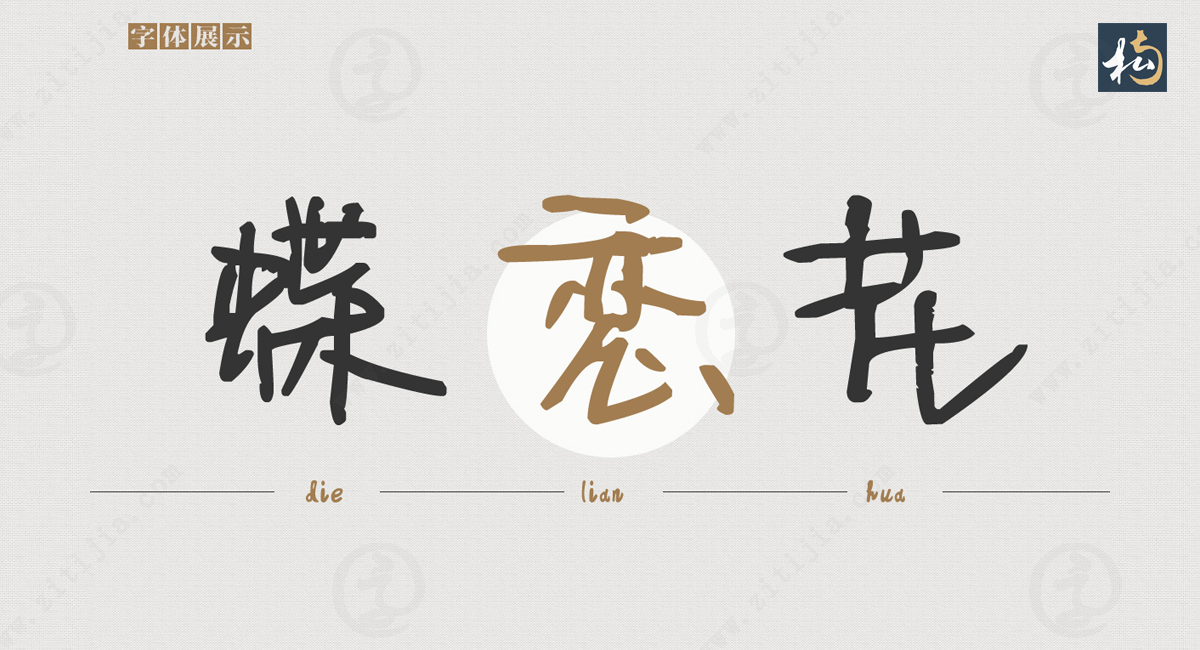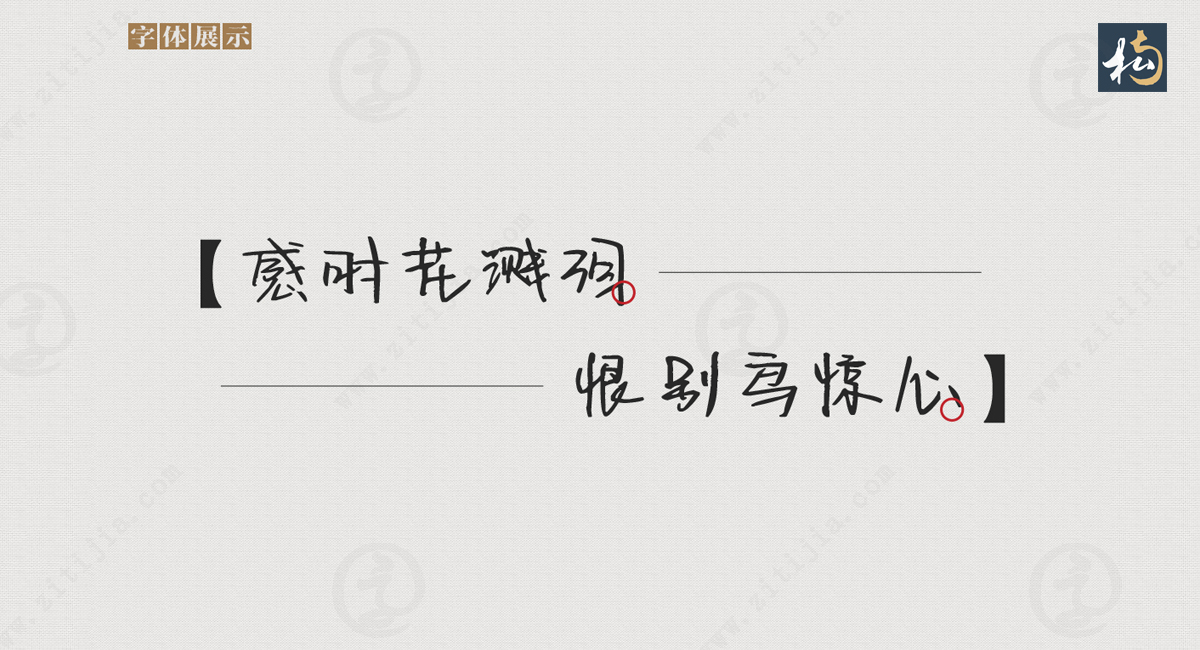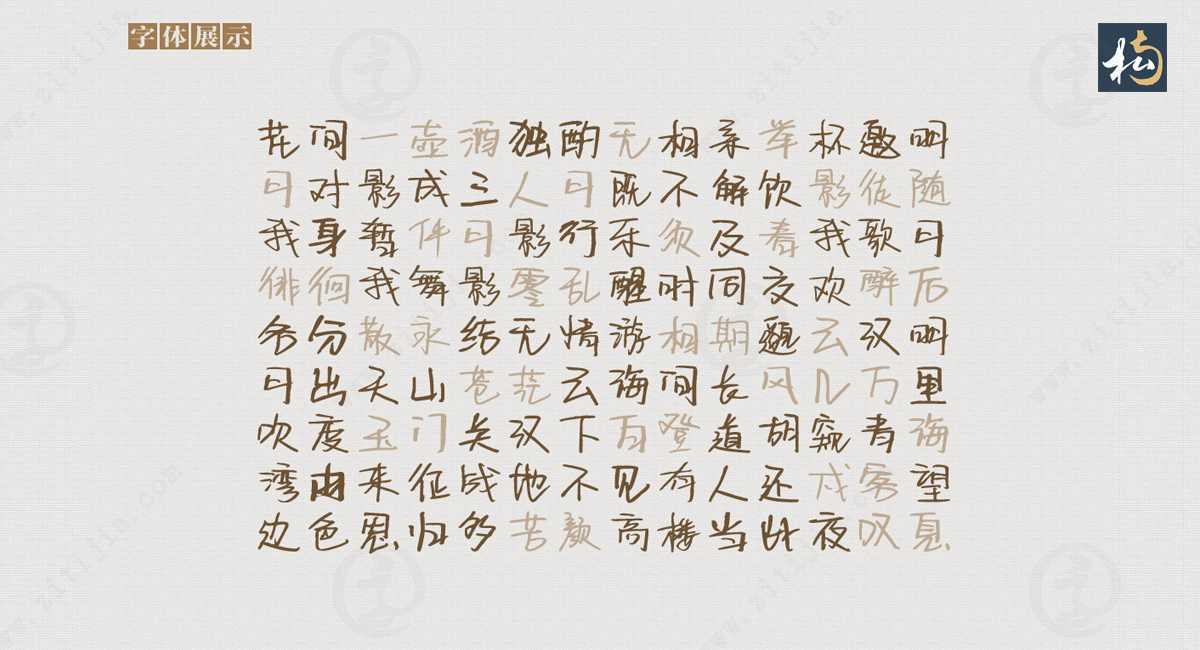
展现独特创意与个性的艺术之美,南构宙华手写字体欣赏
设计风格
在设计领域中,字体的选择对于传达信息和表达情感至关重要。而南构宙华手写字体,则是一款非常独特的字体,它以其流畅自然的字形、富有个性与随性的特点而备受瞩目。这款字体不仅在书写中注重笔画的变化与自由,还充满了笔画的纵横交错,字间空隙适度,使得整个字体看起来非常生动鲜活。
南构宙华手写字体的最大特点之一就是其流畅自然的字形。每一个字母都仿佛是从艺术家的手中流淌而出,没有生硬的笔画转折,更没有僵硬的线条。这种流畅自然的特点赋予了字体一种独特的韵律感,使得文字在视觉上更加动感和有趣。
与此同时,南构宙华手写字体还展现出一定的优美度和品质感。每一个字母都经过精心设计,注重细节的处理,使得字体整体呈现出一种高贵而典雅的气质。这种优美度和品质感使得南构宙华手写字体成为展现文字美感的理想选择。
应用场景
这款字体适用于各种设计领域,尤其是在文艺、时尚和品牌设计中具有独特的优势。对于那些追求独立个性的品牌或者需要突出主题性的宣传资料来说,南构宙华手写字体都能够提供非常好的运用价值。它能够赋予设计作品一种独特的个性和艺术感,使得作品在众多设计中脱颖而出。
无论是印刷品还是数字媒体,南构宙华手写字体都能够展现其独特的魅力。在印刷品上,其流畅的字形和优美的品质感能够为作品增添一份艺术气息,吸引读者的目光。而在数字媒体中,南构宙华手写字体的个性和创意能够为网页、移动应用和社交媒体带来新鲜感和活力。
字体价值
总而言之,南构宙华手写字体是一款独特而富有个性的字体,它以其流畅自然的字形和优美度的品质感而脱颖而出。在各种设计领域中,特别是文艺、时尚和品牌设计中,它能够展现出独特的艺术之美,为作品赋予独特的个性和创意。如果你正在寻找一款能够突出品牌形象或者为作品增添艺术感的字体,不妨考虑南构宙华手写字体,它将为你的设计带来全新的视觉体验。
南构宙华手写